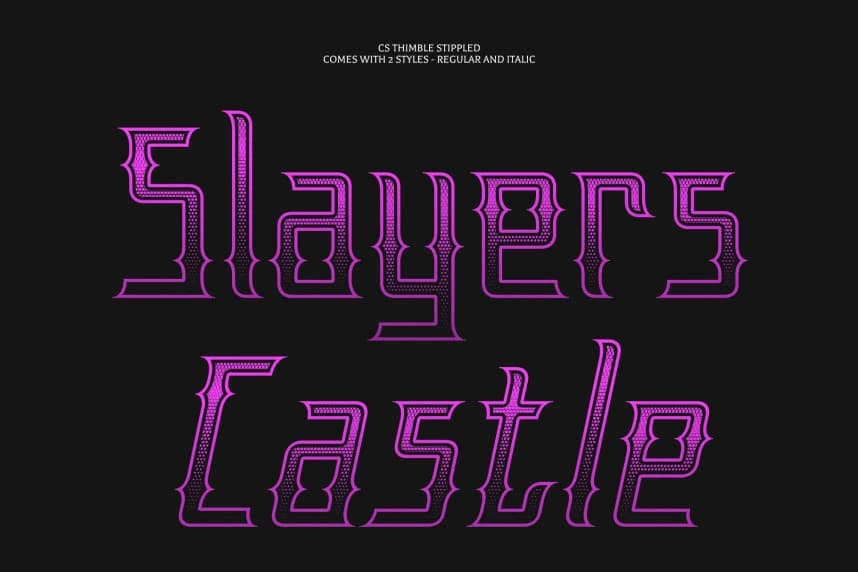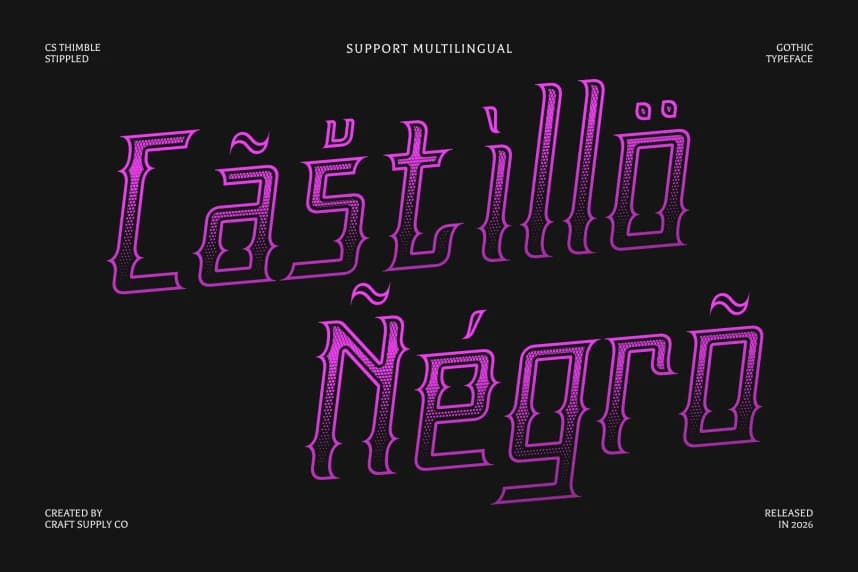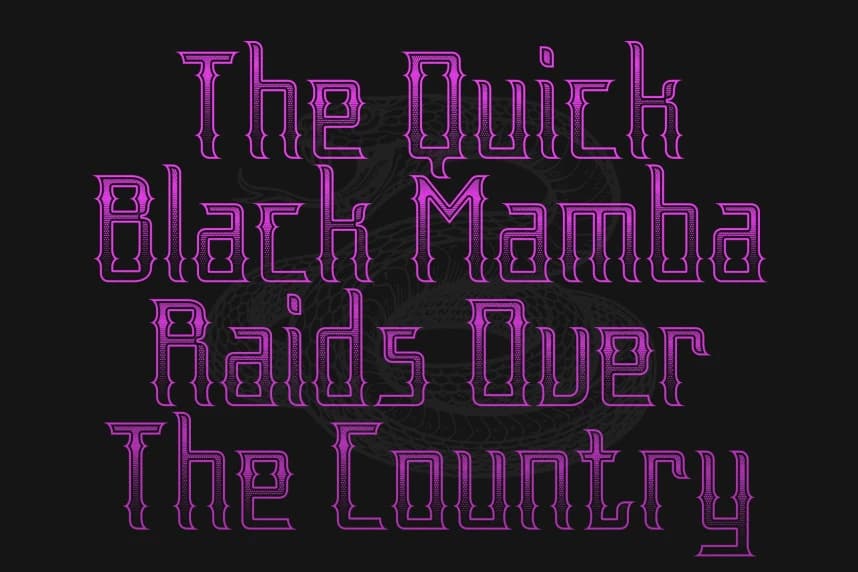
CS Thimble Stippled Font
CS Thimble Stippled Font – Gizemli Dokulu Zarafete Sahip Gotik Fontu, Stipleli Derinliğe Sahip Gotik Stil. Bu, Orta Çağ tipografisinin gizemini ve sanatını akla getiren büyüleyici bir gotik gösterim yazı tipidir.
CS Thimble Stippled Font – Gizemli Dokulu Zarafete Sahip Gotik Yazı Tipi, Stippleli Derinlikli Gotik Stil. Bu, Ortaçağ tipografisinin gizemi ve sanatını çağrıştıran büyüleyici bir gotik gösterim yazı tipidir.